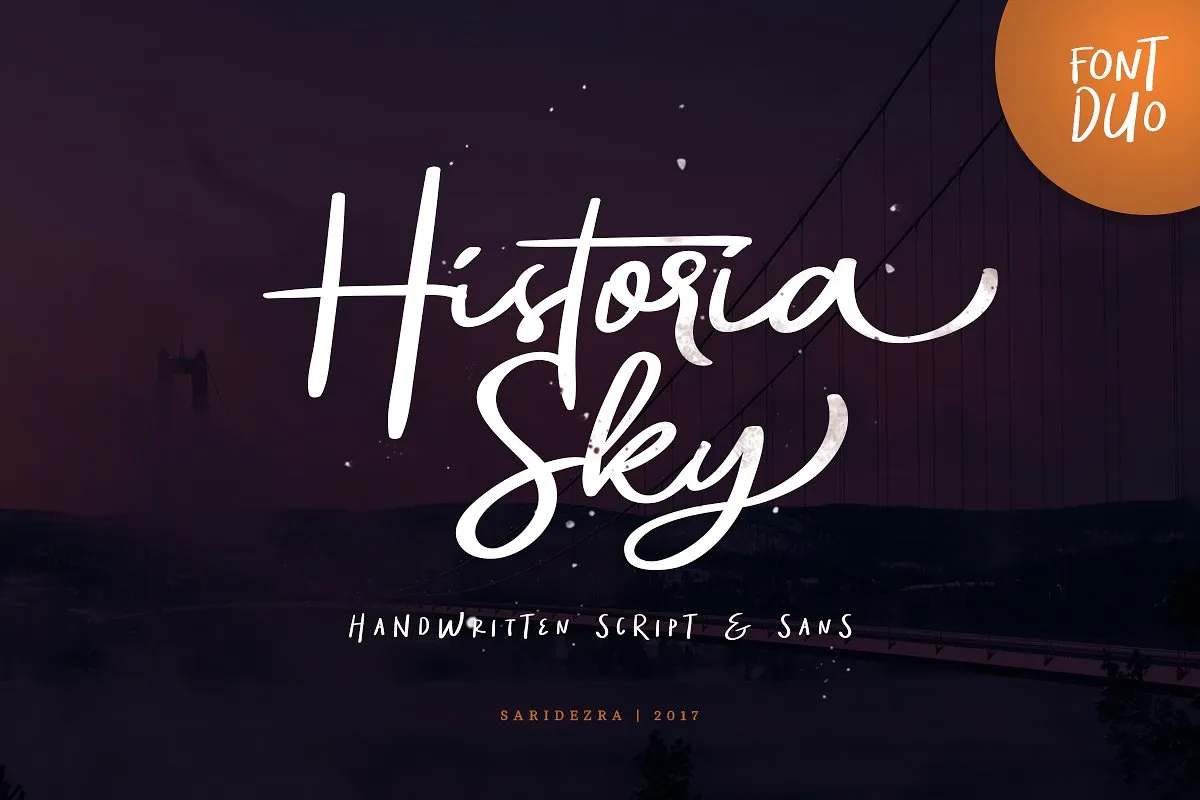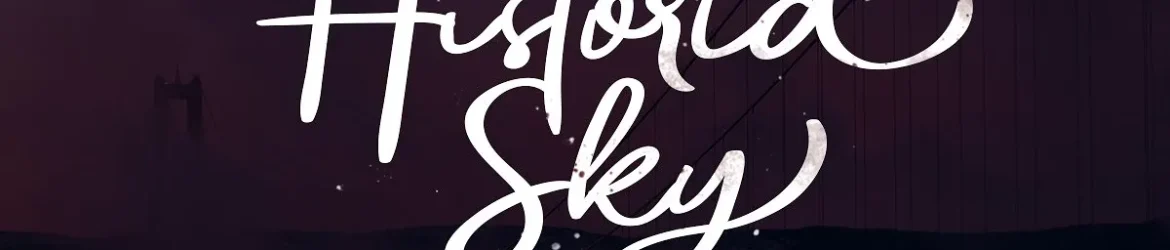
A Historia Sky Font é uma escolha perfeita para quem busca uma maneira criativa de iniciar o novo dia. Introduzida pelo designer Sarid Ezra, esta nova fonte script oferece um ar retrô e autêntico, inspirado em escrita a mão cuidadosamente detalhada. Com alternativas estilizadas, desenhos espécie e ajustes para letra flutuante, você pode criar sua própria assinatura única ou até mesmo fazer uma frase adoravelmente descontraída. Esta fonte script é também um prato cheio para quem gosta de personalizar seu conteúdo digital. Possui múltiplas línguas para atender a diversidade linguística e oferece suporte a OTF e TTF, além de PUA (Programmable Unicode Alternative), tornando-a perfeita para uso em qualquer aplicação gráfica. Seja você um designer de software ou criativo digital, este é o font ideal para aqueles que desejam adicionar uma paleta de cores divertidas ao seu design. Com a Historia Sky Font, sua criação gráfica ganhará vida e personalidade, proporcionando aos seus projetos um toque especial. Trazendo essência e elegância em um formato digital, ela é perfeita para qualquer projeto que você possa imaginar.